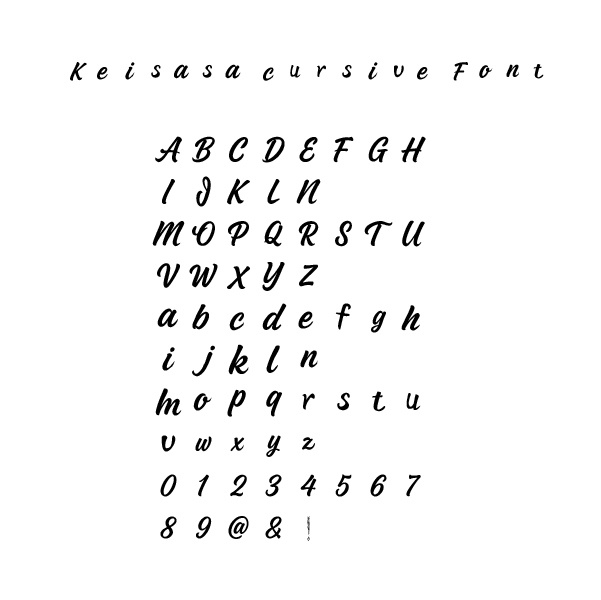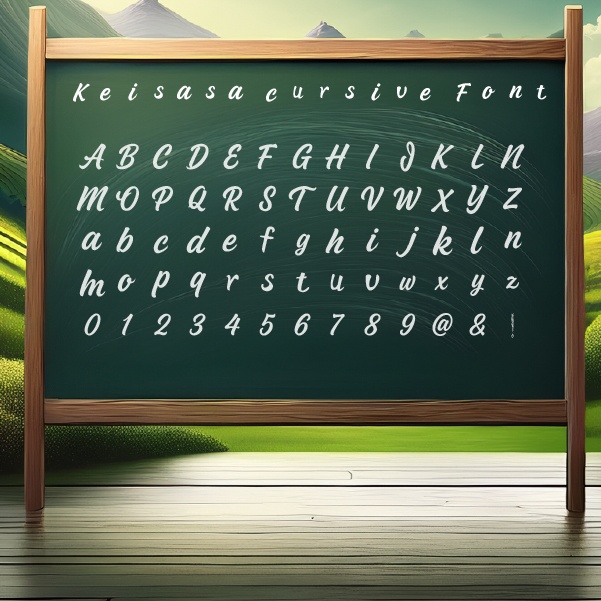
【商用可】Keisasa cursive font|手書き風筆記体フォント
Keisasa Cursive Font|やさしく流れる筆記体フォント Keisasa Cursive Font(ケイササ カーシブ フォント)は、 やわらかく、手書き感のある筆記体風フォントです。 ナチュラルな雰囲気があり、日記や手紙風のデザイン、ロゴ、パッケージなどにおすすめです。 フォント内容 収録文字:英大文字 / 英小文字 / 数字 / 一部記号(@ & ! など) 形式:TrueTypeフォント(.ttf) 商用利用:可能(※利用規約をご確認ください) ⚠️ 利用規約(抜粋) 商用利用可能です 再配布・転売は禁止 著作権は放棄していません Keisasa Cursive Font – Elegant & Friendly Handwriting Description Keisasa Cursive is a stylish, natural-looking handwritten font that adds warmth and personality to your projects. Perfect for journals, packaging, quotes, or branding. Includes uppercase, lowercase, numerals & symbols TTF format Commercial use allowed (see license image for details)